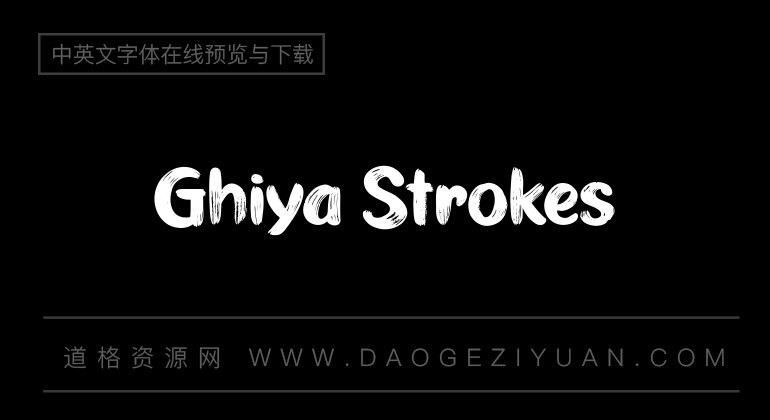
Ghiya Strokes
Ghiya Strokes 字体是一种优雅的手写风格字体。它具有一些独特的特点,如流畅的笔画和轻盈的视觉感受。它是由一位专业的字体设计师设计和制作的,可以用于各种设计项目,如印刷品、海报、广告、名片等。 Ghiya Strokes 字体有多种字重可供选择,包括正常、粗体和斜体,可以根据需要进行选择。此外,它还包括多种语言字符,包括西班牙语、法语、德语、意大利语等,适用于全球各地的不同语言和文化。 总之,Ghiya Strokes 字体是一种非常适合用于具有优雅和现代感的设计项目的字体,无论是印刷品、数字设计还是其他类型的设计项目。
Ghiya Strokes是一款非常不错的手写艺术字体,具有很好的视觉感,适合于文化类的宣传设计、商业类品牌的广告和产品包装设计以及个性化文字排版等较多场景。